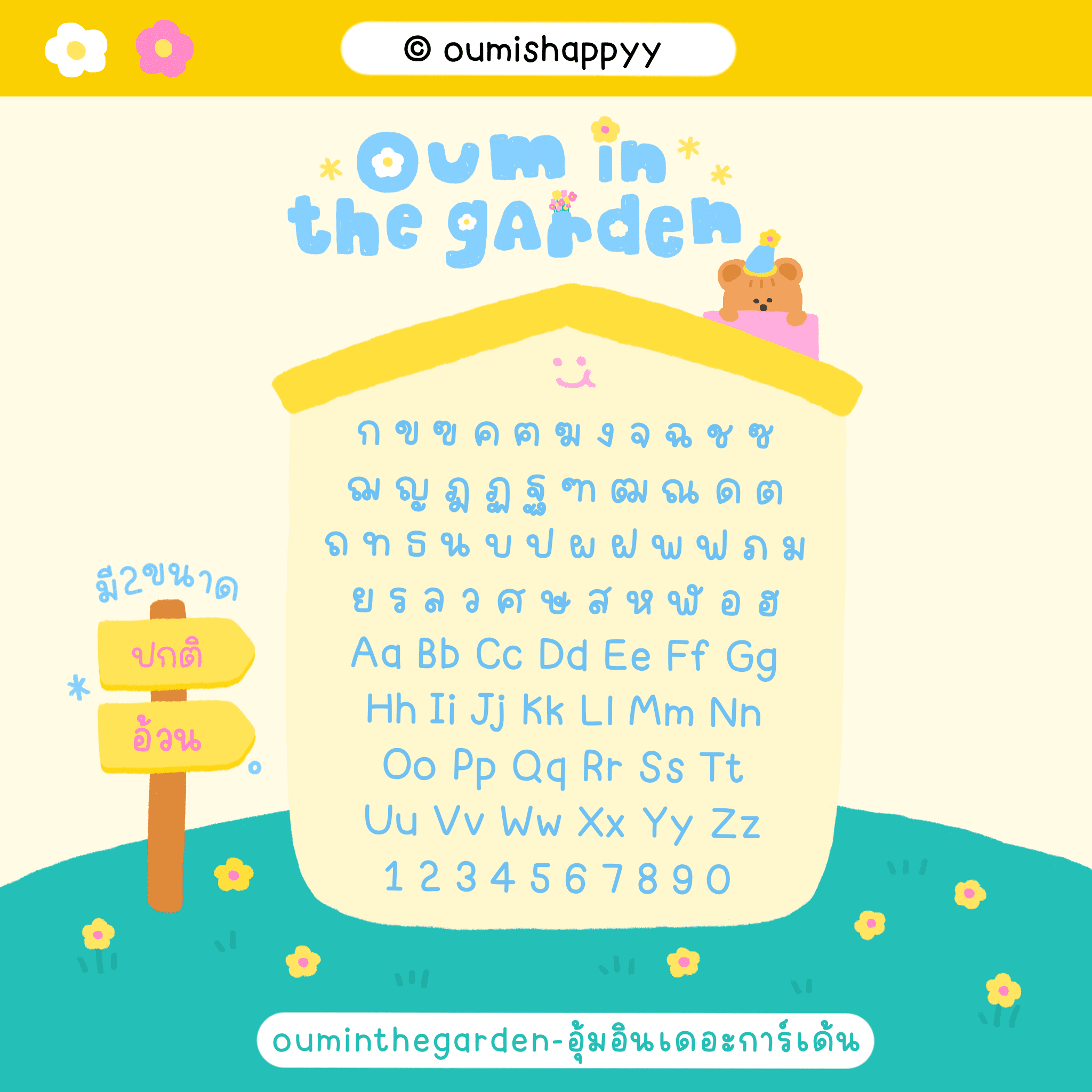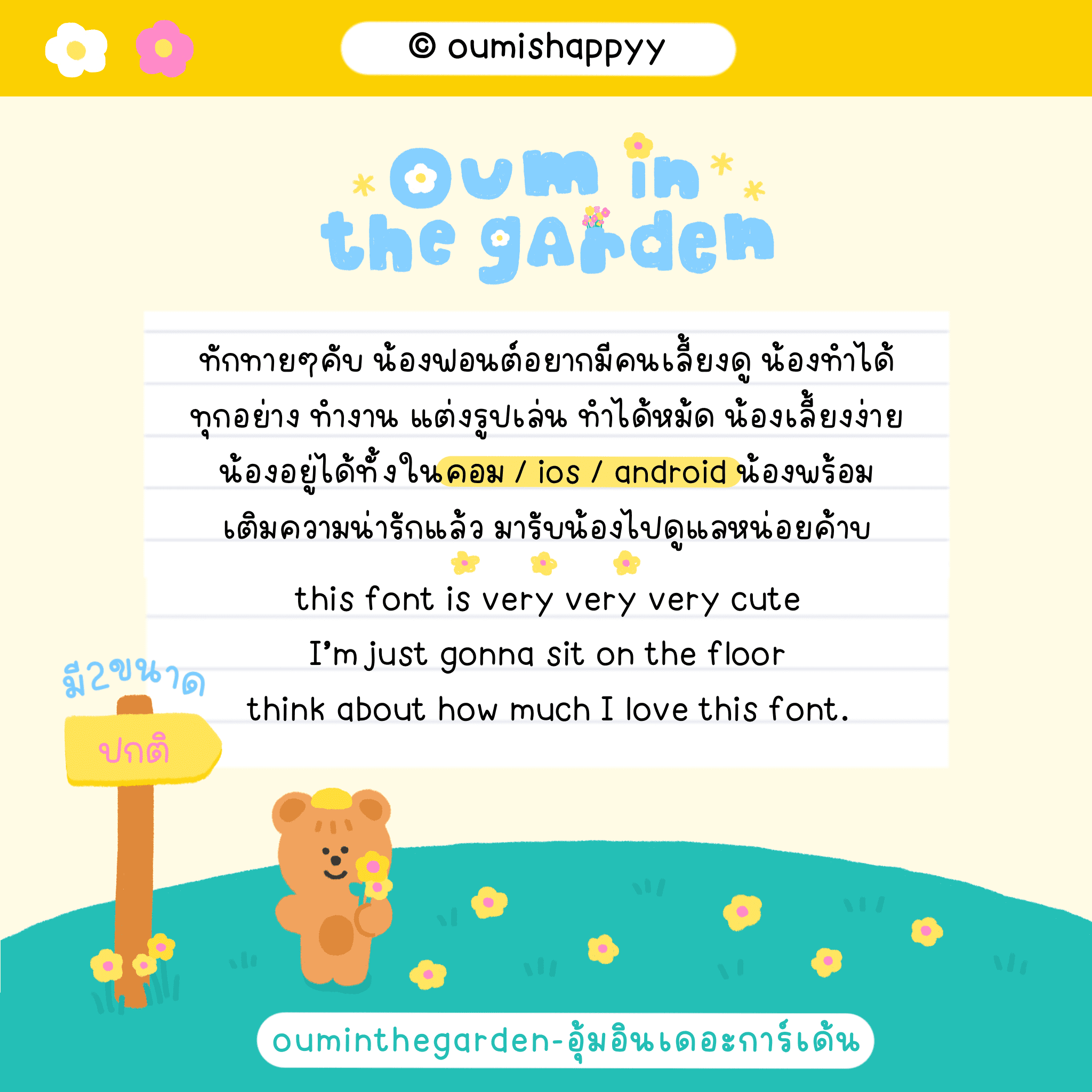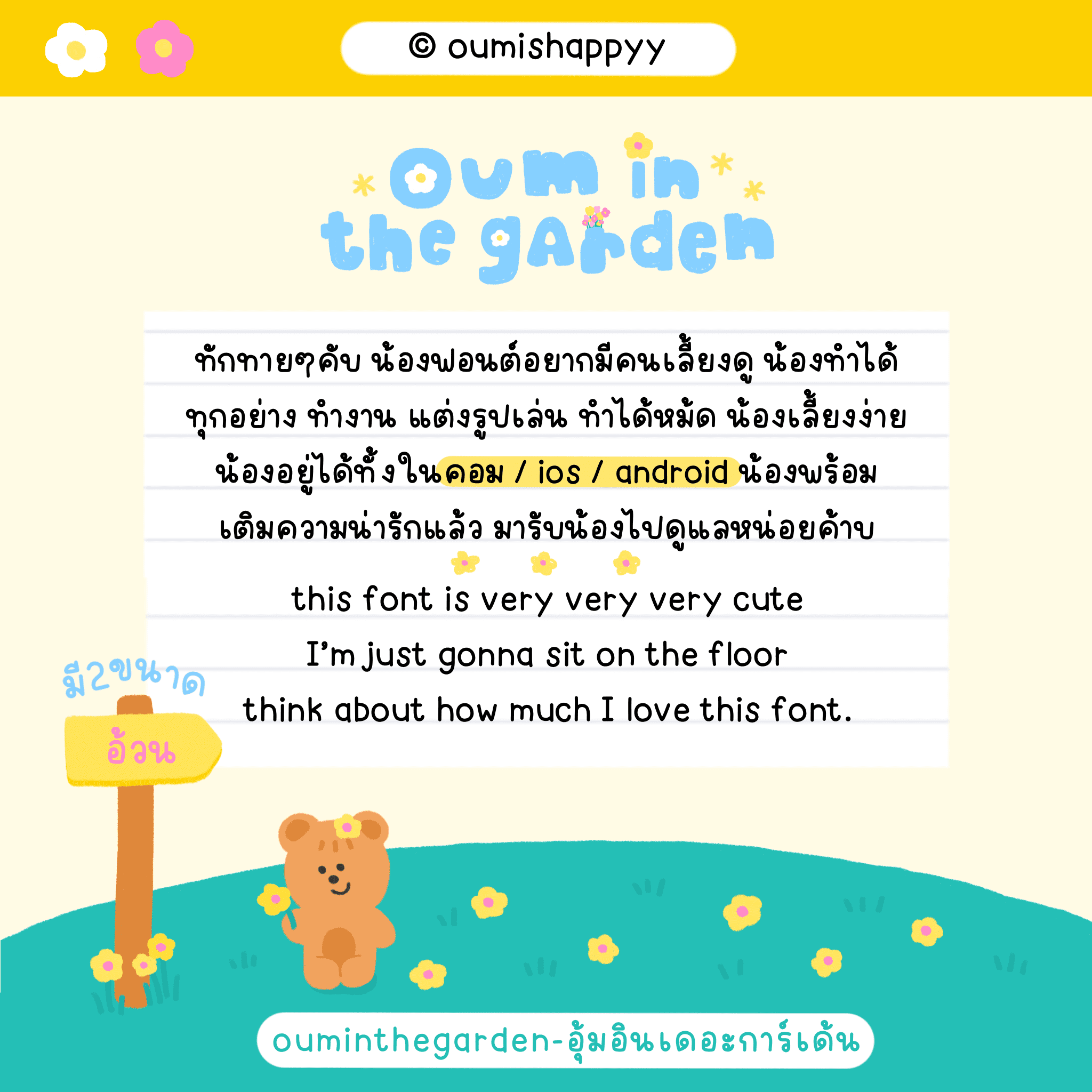
OUMISHAPPYY | FONT (oum in the garden)
น้องคนนี้น่ารักเรียบร้อยมาก ถ้าใครชอบน้อง salmonkids ก็ต้องติดใจน้องคนนี้แน่นอน! เป็นระเบียบจดงานอ่านง่ายมาก เตรียมเอาน้องเข้าลิสต์ฟอนต์
: น้องคนนี้มี2ขนาด ปกติ,อ้วน
มีเลขไทยครบทุกตัว